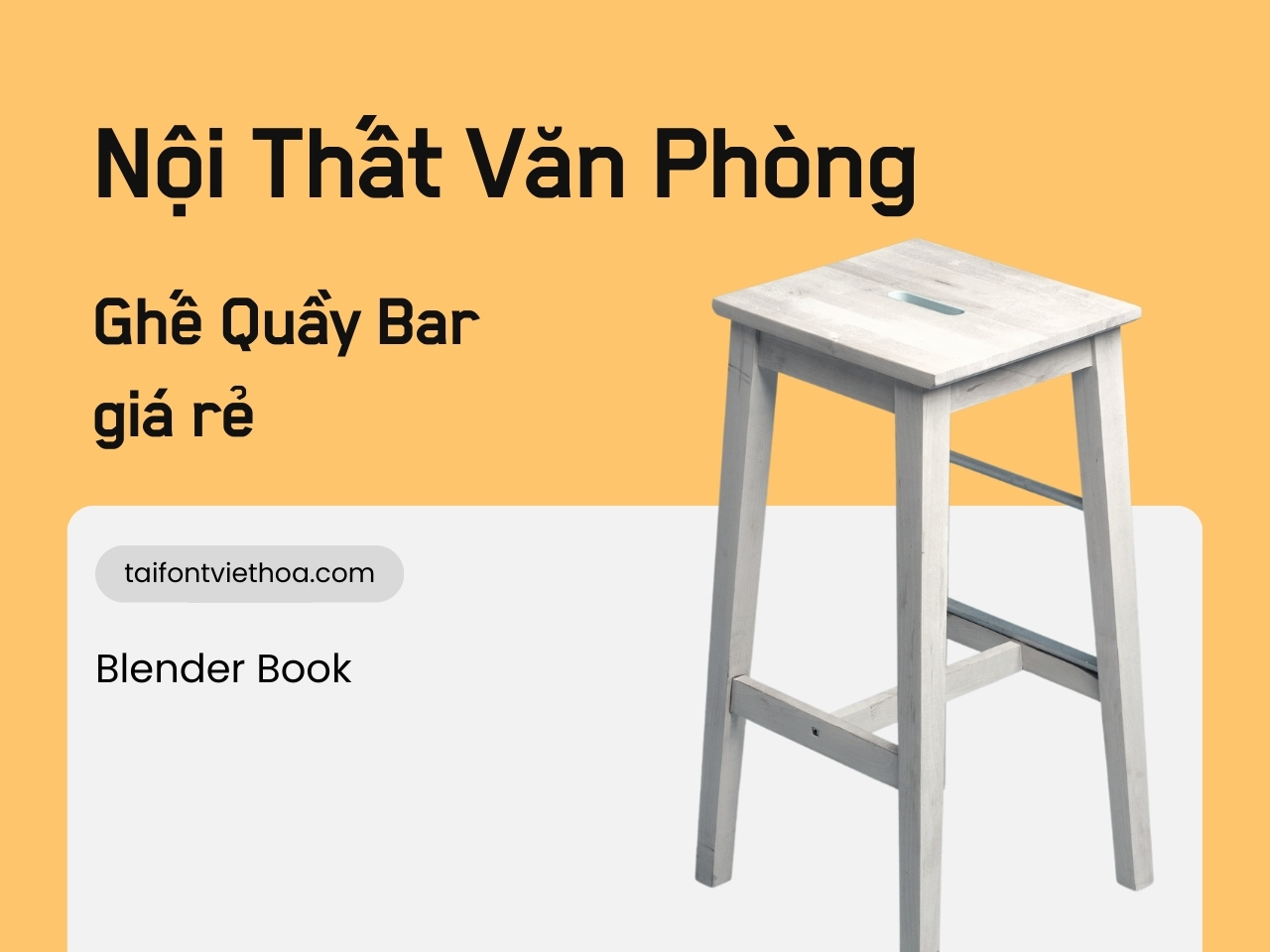
Font việt hóa Blender Book
Giới thiệu font Blender Book – Sans-serif hiện đại và chuyên nghiệp
Blender Book là một font sans-serif hiện đại thuộc họ Blender – bộ font nổi bật bởi kiểu dáng chắc chắn, chuyên nghiệp và dễ ứng dụng trong các thiết kế thương hiệu. Font được biết đến với khả năng truyền tải thông điệp rõ ràng, sắc nét, rất phù hợp trong các môi trường cần tính trực quan cao như giao diện kỹ thuật số, truyền thông và in ấn. Phiên bản Việt hóa do Zenis thực hiện, giúp font hỗ trợ đầy đủ tiếng Việt cùng hơn 100 ngôn ngữ phổ biến khác. Font này đã được taifontviethoa.com sưu tầm và lựa chọn, nhằm phục vụ cộng đồng thiết kế Việt với nhu cầu sử dụng trong branding, tiêu đề, banner và các ấn phẩm hiện đại cần sự gọn gàng, tối giản và dễ đọc.
Đặc điểm thiết kế chuyên nghiệp và ứng dụng của font Blender Book
Blender Book có cấu trúc sans-serif rõ ràng với nét chữ dày vừa phải, các góc bo nhẹ nhưng vẫn giữ cảm giác chắc chắn và hiện đại. Kiểu chữ này nổi bật nhờ sự cân đối về tỷ lệ, độ cao chữ đều, tạo trải nghiệm thị giác ổn định và dễ chịu. Font đặc biệt phù hợp cho thiết kế logo, tiêu đề bài viết, giao diện web, ứng dụng di động, ấn phẩm quảng cáo và bảng hiệu nhận diện thương hiệu. Với phong cách trung tính và dễ ứng dụng, Blender Book rất phù hợp trong các ngành như bất động sản, công nghệ, thương mại điện tử, giáo dục và quảng cáo. Đây là font sans-serif lý tưởng cho các nhà thiết kế yêu thích sự rõ ràng và hiệu quả thị giác cao.